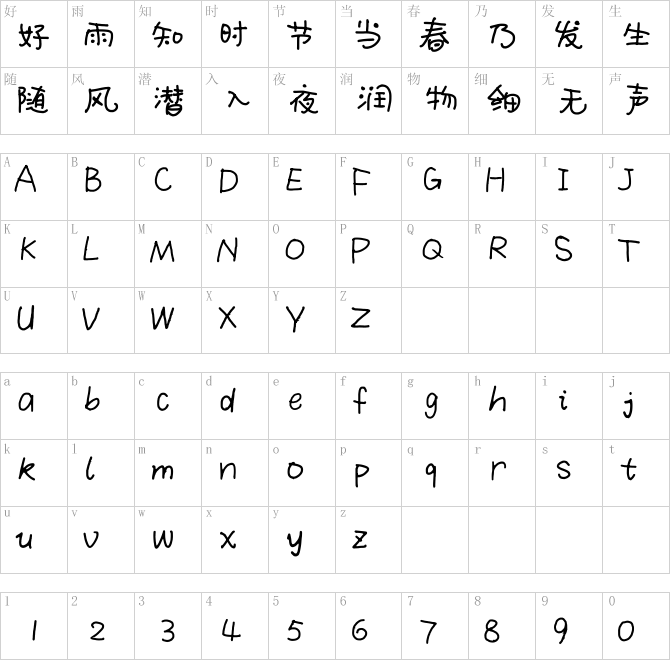
默陌歪歪纤瘦体.ttf,这款字体结构工整、笔画清晰,兼顾美观与易读性,适用于标题、正文、海报、包装、LOGO 等多种场景。字形优雅稳定,风格百搭耐看,适配日常排版与创意设计,让文字呈现更舒适、更具质感。默陌歪歪纤瘦体.ttf一笔一画,皆是细节,以均衡的比例、流畅的线条打造舒适视觉体验,字形端正大气,风格简约现代。无论是商业设计、品牌宣传还是日常排版,都能轻松驾驭,让文字更有格调与力量。默陌歪歪纤瘦体.ttf字体下载。
默陌歪歪纤瘦体.ttf是一款默陌字库出品的书法字体,目前已经发布了50款+字体